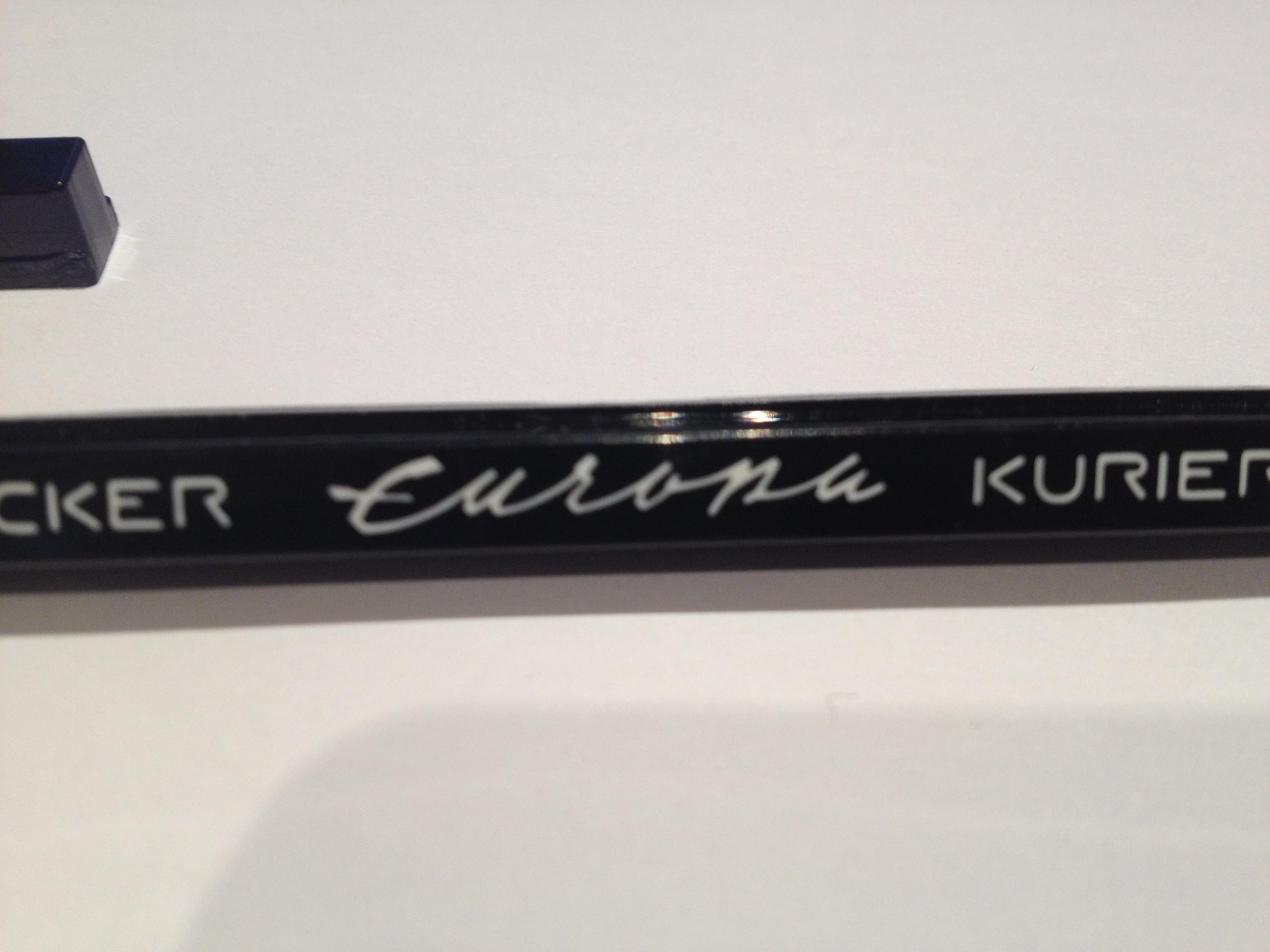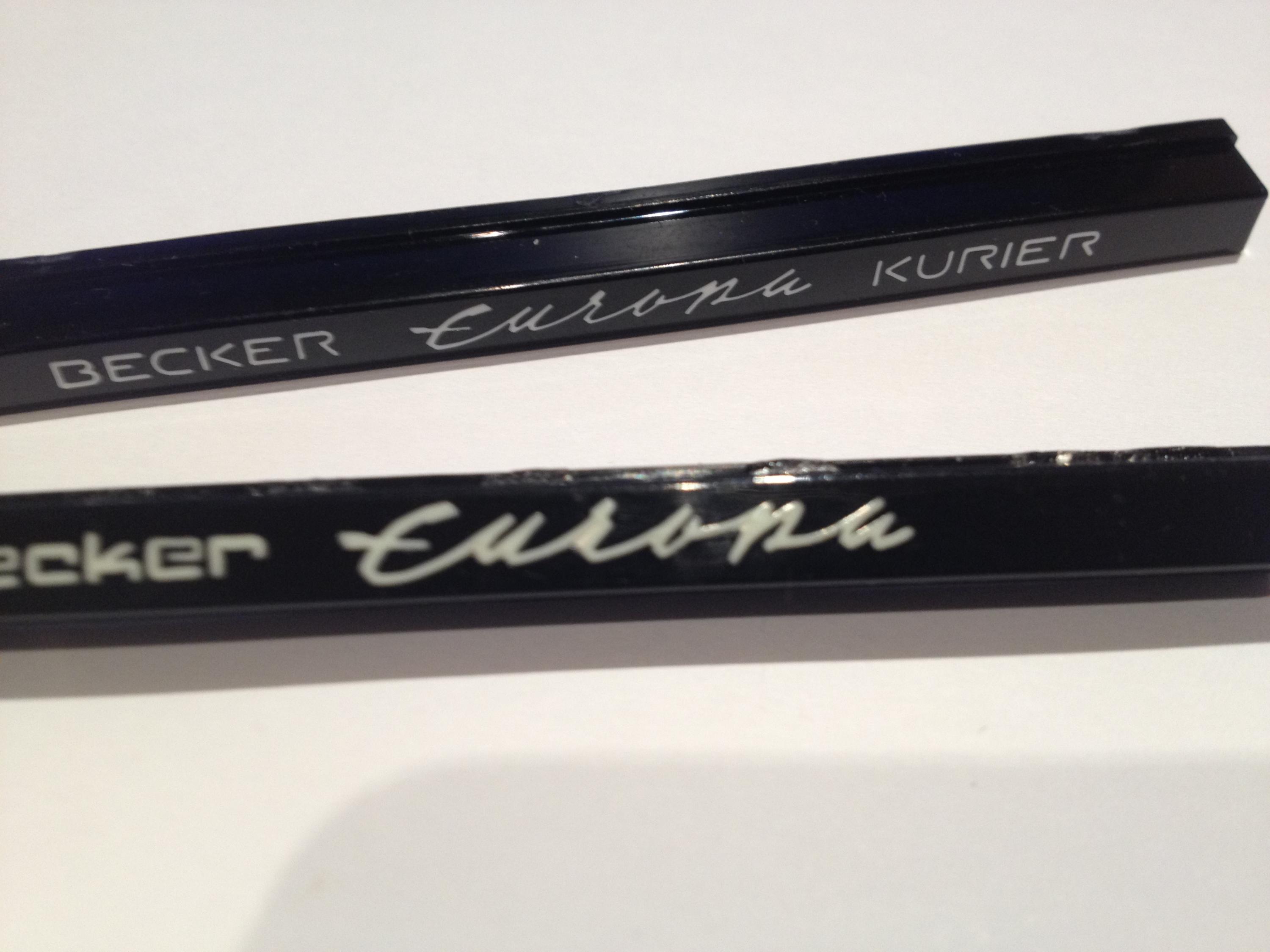
Schrift für Oldtimer Radio von Becker
Ich habe stundenlang gesucht. 400 Seiten Fonts durchgeschaut, "What the Font" befragt, "What font is..", leider keine Ergebnisse :-(
Auf alten Autoradios (bzw. den Blenden) der Firma Becker stehen verschiedene Schriftzüge: "Europa", "Grand Prix", "Mexico"
Kennt jemand diese Schrift!
Gelöst von CLMNZ
Schon die unterschiedlichen Verbindungshöhen deuten darauf hin, dass das kein Font ist, sondern – wie Clmnz schon  vermutet – handgeschrieben ist.
Die Schrift kam mir bekannt vor, erinnerte ein bisschen an alte Letraset-Zeiten, aber da habe ich mich wohl getäuscht.
an den TE – was willst du mit der Schrift machen ?
Radio restaurieren ?
Im Grunde kann man den Schriftzug ja einscannen und nachbauen ...
Ja du hast Recht!
Ein Kunde von mir restauriert Oldtimer. Er möchte aber keine schwarze Blende haben, sondern eine weiße Blende mit Originalschriftzug. (Oldtimerliebhaber sind Perfektionisten, da muss alles bis ins kleinste Detail stimmen)
Bin jetzt dabei alles einzuscannen und nach zu bauen.